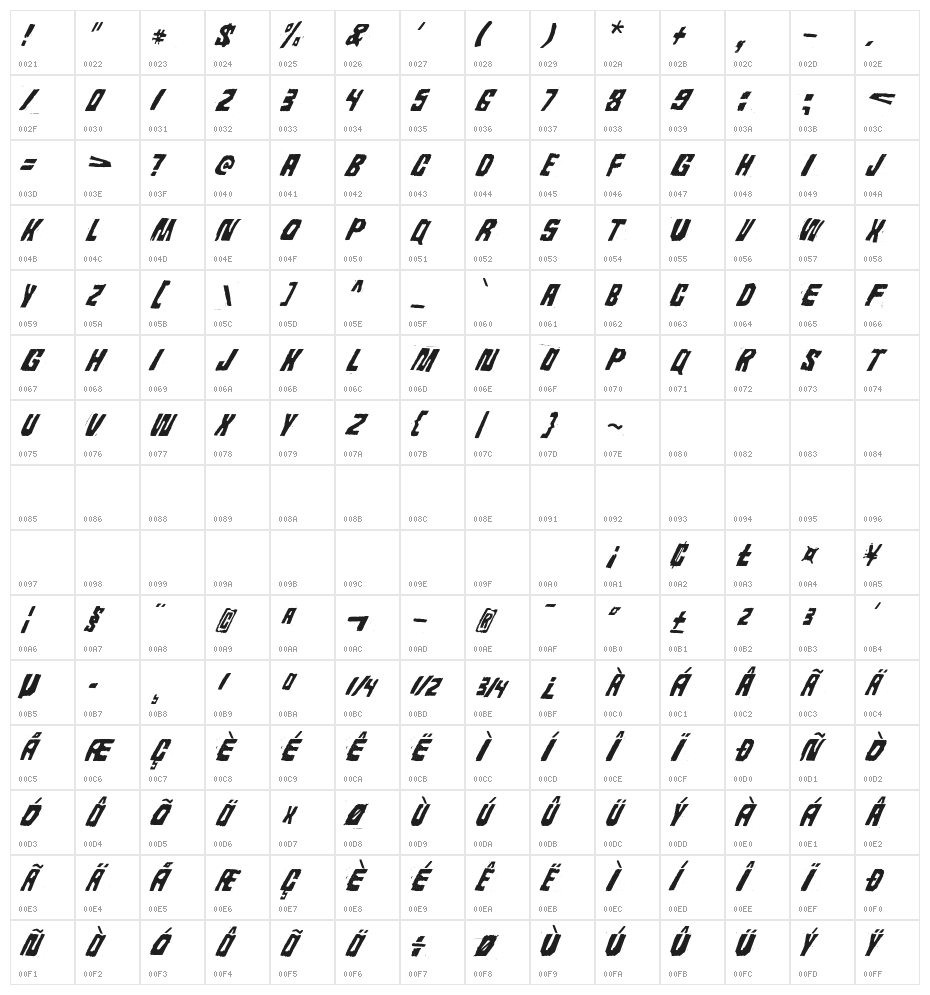
Androidi Pisa Font
| Stile generale | Modern, Edgy |
| Progetti proposti | Ideal for sports branding, action movie posters, edgy fashion labels, or any project needing a bold, energetic typeface. |